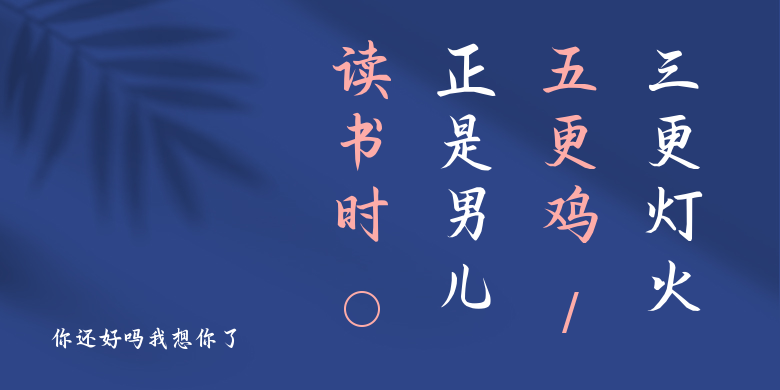
你还好吗我想你了
你还好吗我想你了,这款字体结构工整、笔画清晰,兼顾美观与易读性,适用于标题、正文、海报、包装、LOGO 等多种场景。字形优雅稳定,风格百搭耐看,适配日常排版与创意设计,让文字呈现更舒适、更具质感。你还好吗我想你了一笔一画,皆是细节,以均衡的比例、流畅的线条打造舒适视觉体验,字形端正大气,风格简约现代。无论是商业设计、品牌宣传还是日常排版,都能轻松驾驭,让文字更有格调与力量。你还好吗我想你了字体下载。